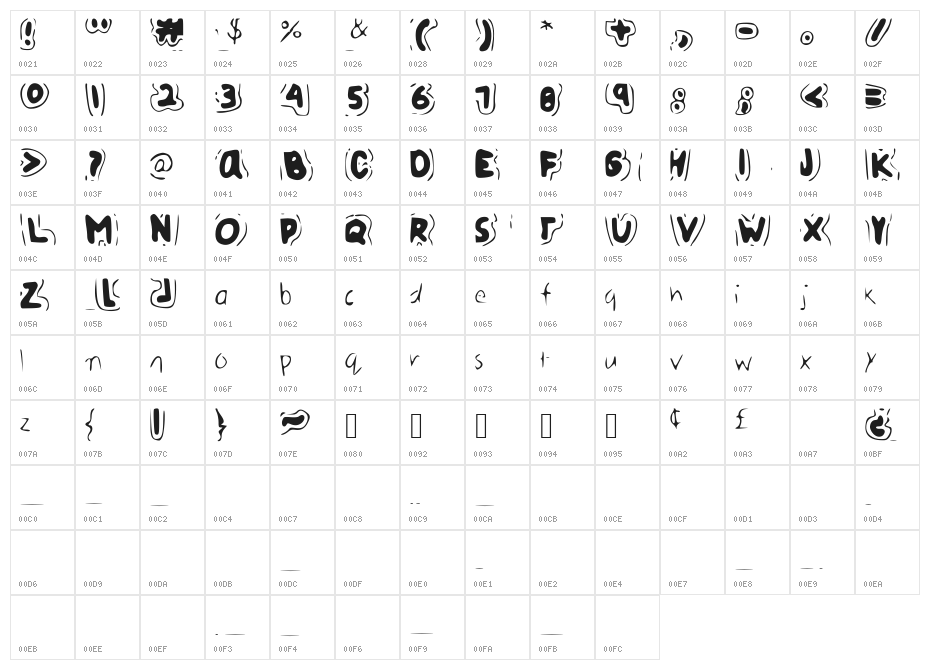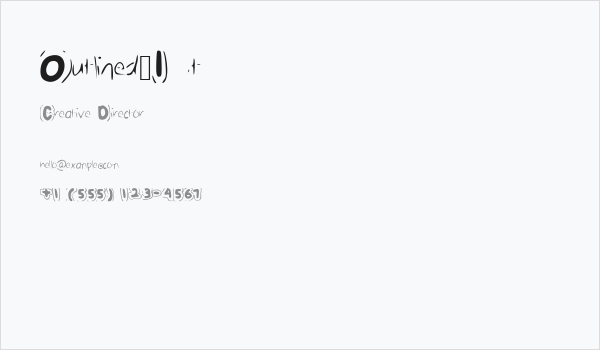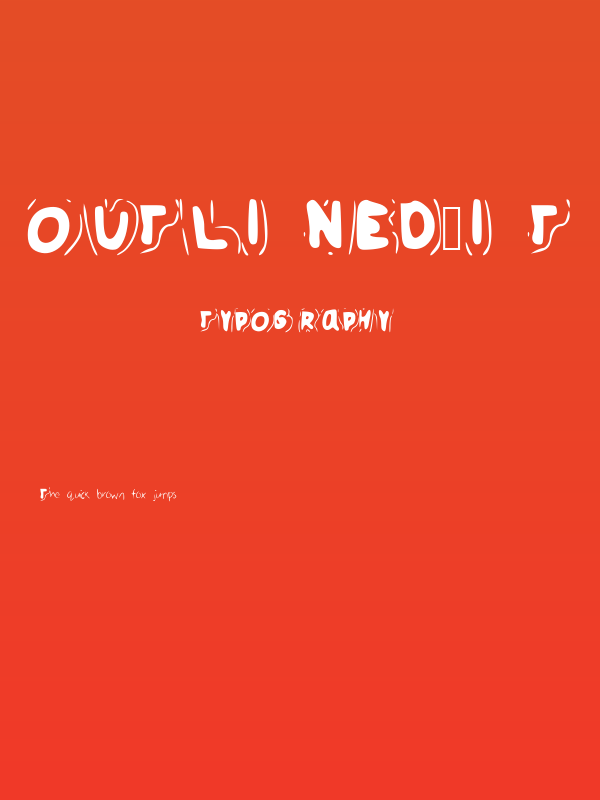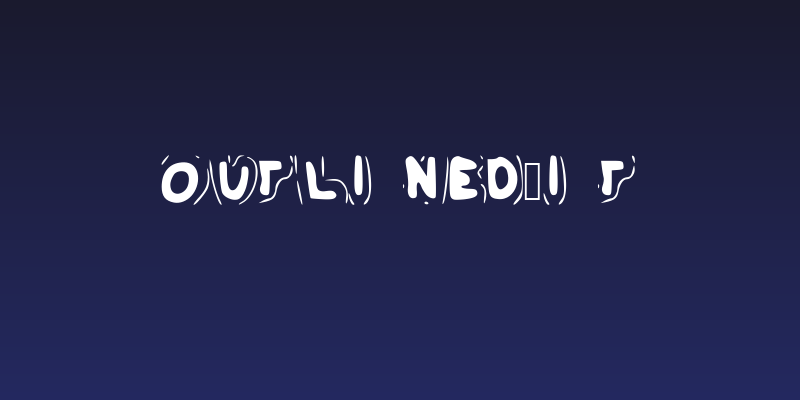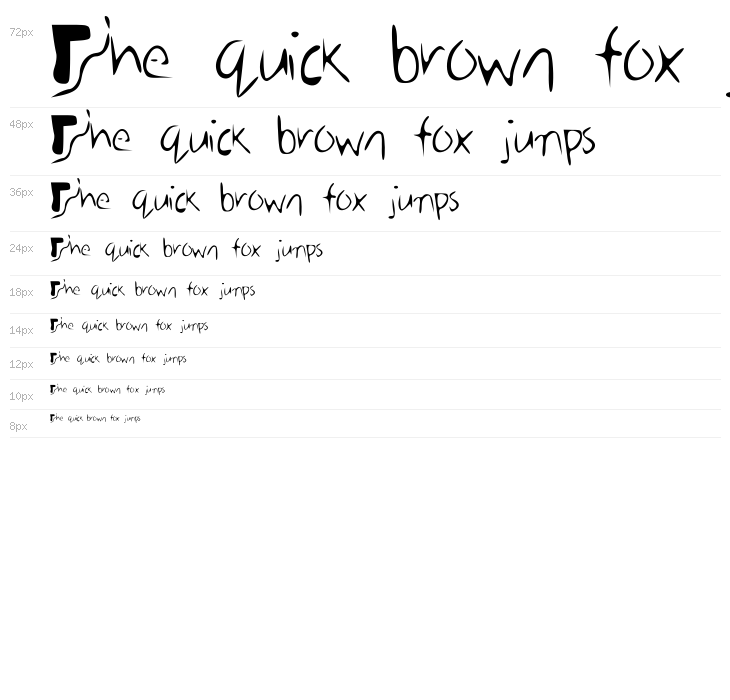
Outlined_It Font
| Stile generale | Modern, Artistic |
| Progetti proposti | Ideal for creative projects such as posters, album covers, children's books, and branding for artistic ventures. |